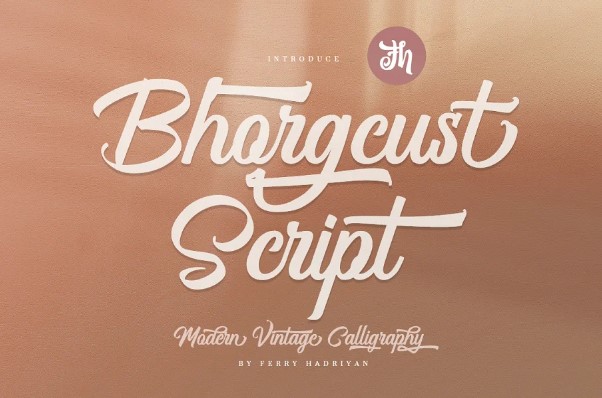
Creativemarket Bhorgcust - Script Font
[Creativemarket] Bhorgcust Font
Bhorgcust - это великолепный и смелый рукописный шрифт, созданный, чтобы придать стильный штрих вашим заголовкам и логотипам проектов.
Этот шрифт читается как сильный, уверенный и динамичный и может придать тонны ностальгического характера вашим дизайнерским работам.